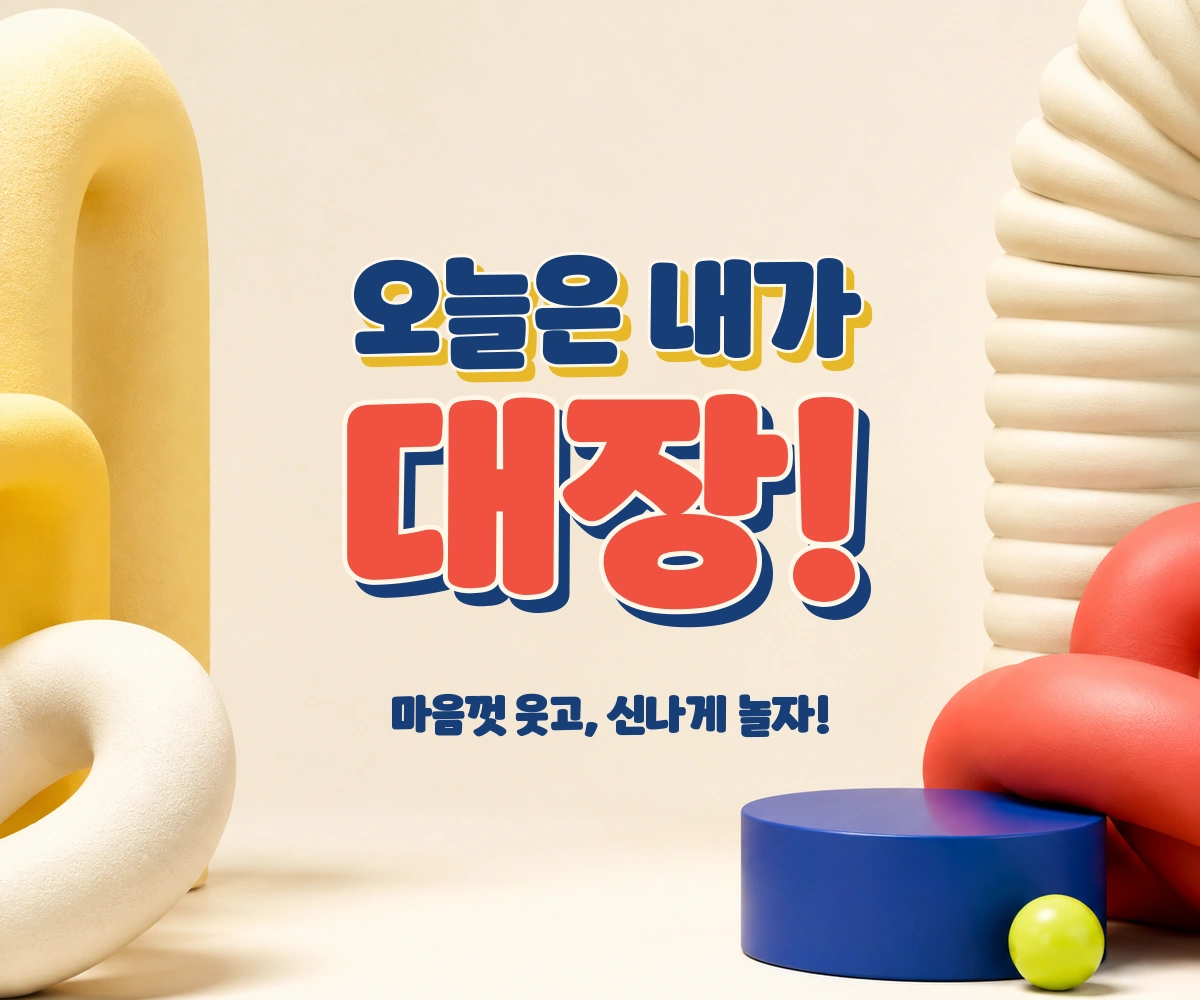
뚠뚠이 — (주)와이즈폰트에서 배포하는 무료 폰트입니다. 동글동글하고 통통한 글자 형태가 돋보이는 귀여운 손글씨체
와이즈폰트가 2020년에 내놓은 손글씨 서체입니다. 제작사는 이 서체를 동글통통 귀여운 손글씨 폰트라고 소개하면서 제목용과 자막용으로 잘 어울린다고 밝혔습니다.
파일을 열어 재어 보면 그 설명이 맞습니다. 획이 굵고 속이 꽉 차서 자면을 채우는 비율이 0.46에 이릅니다. 폰트픽에 올라온 같은 굵기의 한글 서체 138종 가운데 열 번째로 진한 축입니다. 낱자는 높이보다 폭이 넓어 가로로 퍼져 있고, 받침이 붙어도 글자 높이가 거의 변하지 않는 네모틀이라 굵은 획에도 글줄이 흐트러지지 않습니다.
한 가지 미리 확인하실 것이 있습니다. 이 서체의 한글은 2,574자입니다. 완성형 11,172자를 다 담은 것이 아니라 흔히 쓰는 글자 위주로 골라 넣은 것이라 드문 음절이 들어가면 네모로 빠집니다. 정해진 문구를 조판할 때는 문제가 없지만 이름이나 주소처럼 어떤 글자가 올지 모르는 자리에는 미리 확인하고 쓰세요. 굵기는 하나입니다.